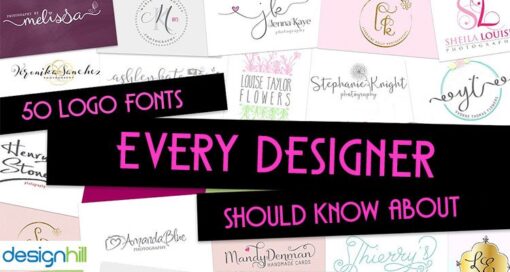
25 Font Logo yang Harus Diketahui Setiap Desainer
‘Jenis desain adalah tentang fungsi. Menggambar bentuk yang bagus saja tidak cukup. ‘ – James Todd Seringkali kita memikirkan warna dan gambar dalam desain grafis, terutama dalam logo. Tetapi font logo adalah elemen desain yang sama pentingnya. Bahkan, banyak logo perusahaan ikonik berbasis tipografi. Jika logo memiliki nama bisnis, keberhasilan desainnya tergantung pada penggunaan font yang … Continue reading 25 Font Logo yang Harus Diketahui Setiap Desainer